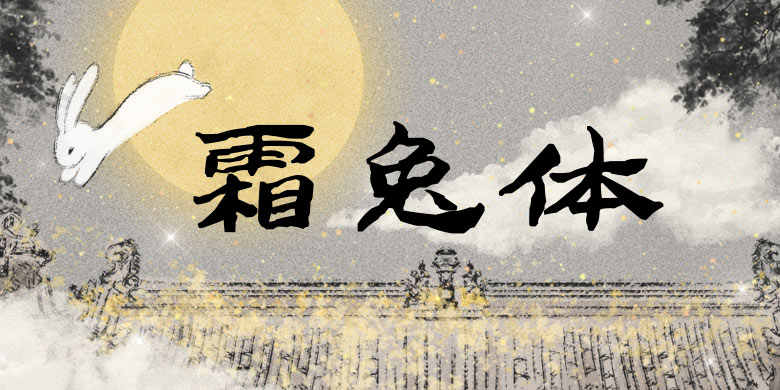
方正手迹-霜兔体
方正手迹-霜兔体,这款字体结构工整、笔画清晰,兼顾美观与易读性,适用于标题、正文、海报、包装、LOGO 等多种场景。字形优雅稳定,风格百搭耐看,适配日常排版与创意设计,让文字呈现更舒适、更具质感。方正手迹-霜兔体一笔一画,皆是细节,以均衡的比例、流畅的线条打造舒适视觉体验,字形端正大气,风格简约现代。无论是商业设计、品牌宣传还是日常排版,都能轻松驾驭,让文字更有格调与力量。方正手迹-霜兔体字体下载。
该款字体对隶书进行了大胆的创新,不仅加入了楷书的一些笔意,也能看到行书的一些影子。因此该字既有隶书的厚重感,行书爽利感,又有楷书中正平各。适用于现代诗歌、短文的排版,以及文化、商业类品牌的广告语设计。